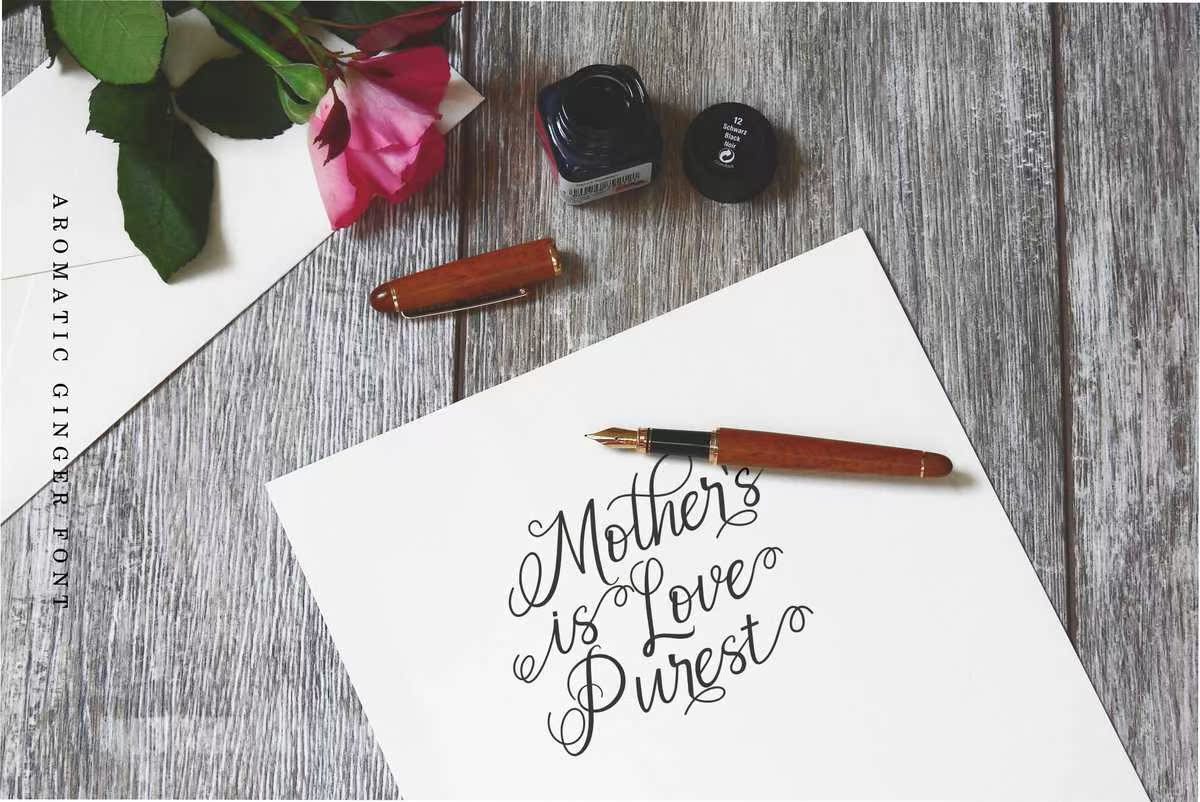
简介一种优雅的书法字体,名为芳香姜。这种字体由双铅笔笔画设计而成,每种笔画都采用水洗、剪裁和TC等系统化的字体。芳香姜笔画完美地体现了婚卡、婚礼庆典、标识、个人品牌、,签名和更多。介绍一种优雅的书法字体,名为芳香姜。该字体由双铅笔笔画设计,每种笔画都采用水洗、剪裁和TC等系统样式。芳香姜笔画是结婚卡、婚礼宣传、标识、个人品牌、签名和更多功能的完美选择。